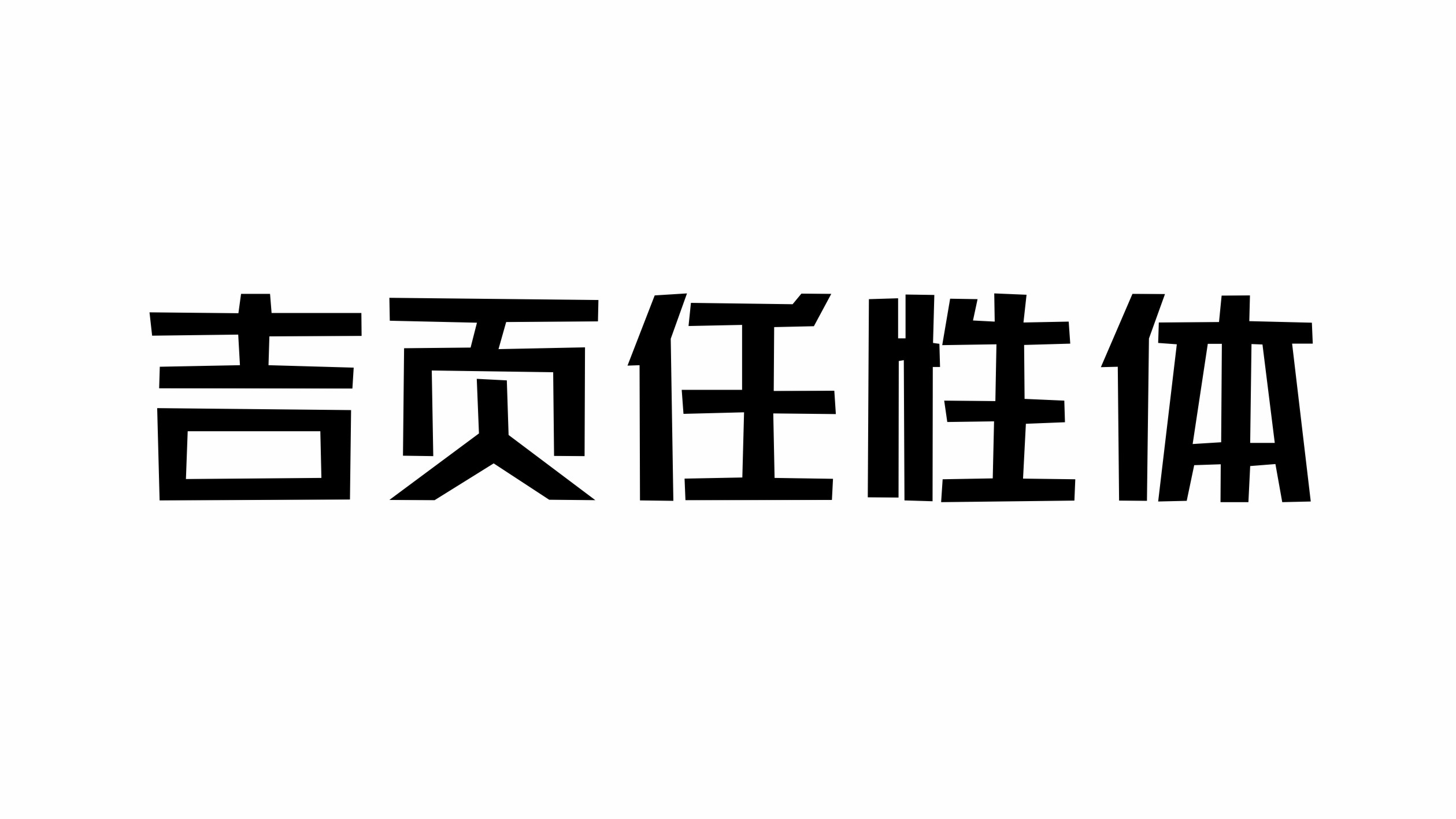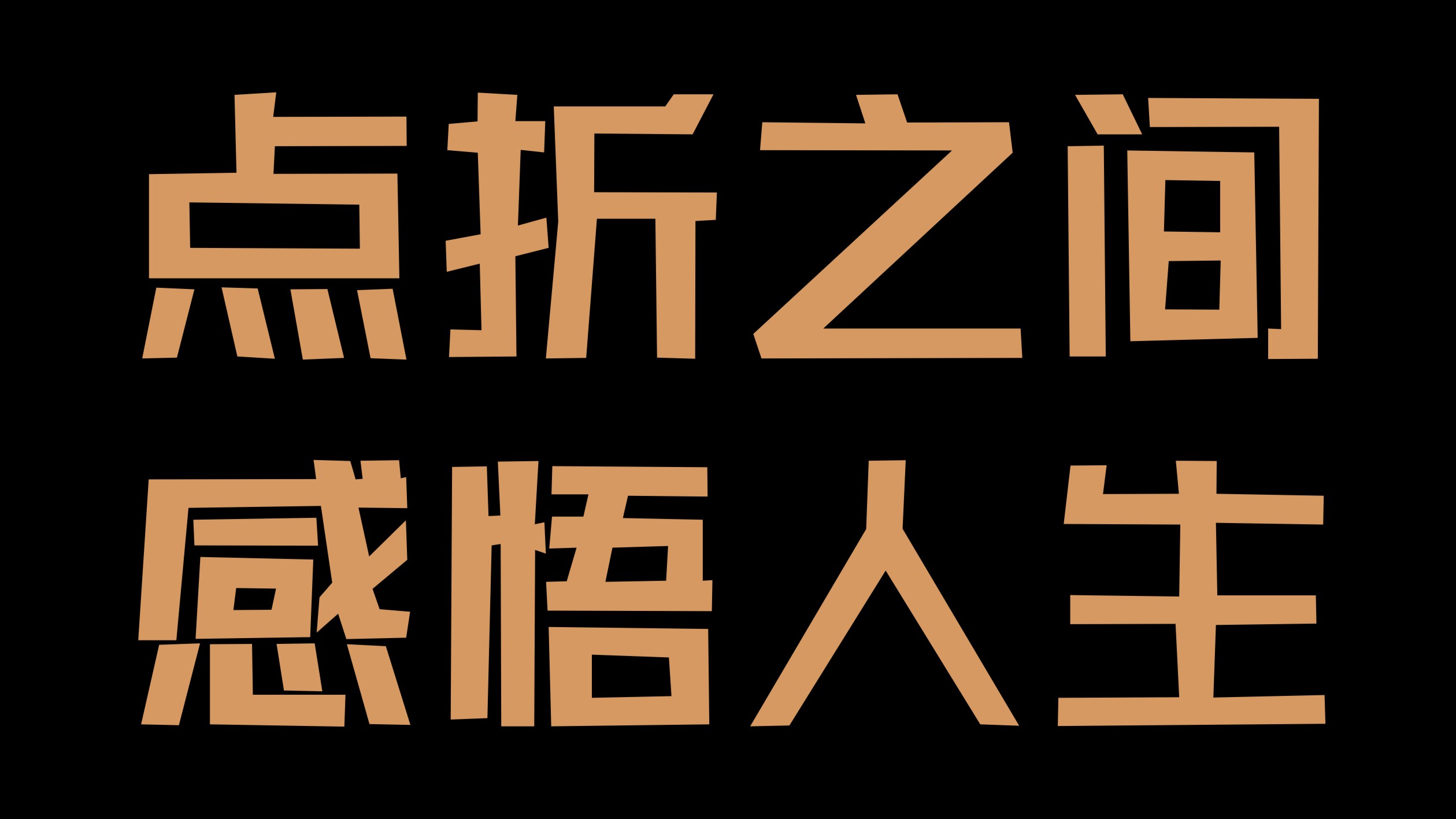
吉页字库“四”款新字体上线了
吉页燃爆体:是一款手写字体。因字体笔触又有爆炸的效果,起爆炸体又太爆力,于是“吉页燃爆体”诞生了。吉页任性体:因其笔画并非横平竖直,一笔下来粗细也并非一致,而是稍微有些随性,我们姑且认为它是任性吧。吉页非宋体:该字体横画有宋体风格的衬线,但又区别于宋体,想来想去干脆就叫“吉页非宋体”吧。吉页冰墩墩体:字体笔画的始端与末端都以弧形表现,整体圆墩墩的,且笔画又似“熊猫”的臂与腿,就想起了北京冬季奥运会吉祥物“冰墩墩”的造形,于是“吉页冰墩墩体”与大家见面了。
吉页燃爆体:是一款手写字体。因笔画风格有左右两边向上翘的姿态,似一双翅膀,所以最初想起名叫“吉页双飞体”的,但突然间感觉哪里不太对劲儿,似乎有点不健康的感脚,于是果断pass掉了。因字体笔触又有爆炸的效果,起爆炸体又太爆力,于是“吉页燃爆体”诞生了。我们这款字体就是一款手写体,请大咖们不要拿书法来作比较,能运用到适合的场景,展示出应有的效果就能体现出字体的魅力。
吉页任性体:因其笔画并非横平竖直,一笔下来粗细也并非一致,而是稍微有些随性,我们姑且认为它是任性吧。
吉页非宋体:下面这一行字的上部像不像钟大人的帽饰?本来想把字体名称叫钟大人的名字的,但又害怕钟大人生气,所以还是放弃了这个想法。该字体横画有宋体风格的衬线,但又区别于宋体,想来想去干脆就叫“吉页非宋体”吧,哈哈哈……后来觉得名字还是不错的。
吉页冰墩墩体:字体笔画的始端与末端都以弧形表现,整体圆墩墩的,且笔画又似“熊猫”的臂与腿,就想起了北京冬季奥运会吉祥物“冰墩墩”的造形,于是“吉页冰墩墩体”与大家见面了。